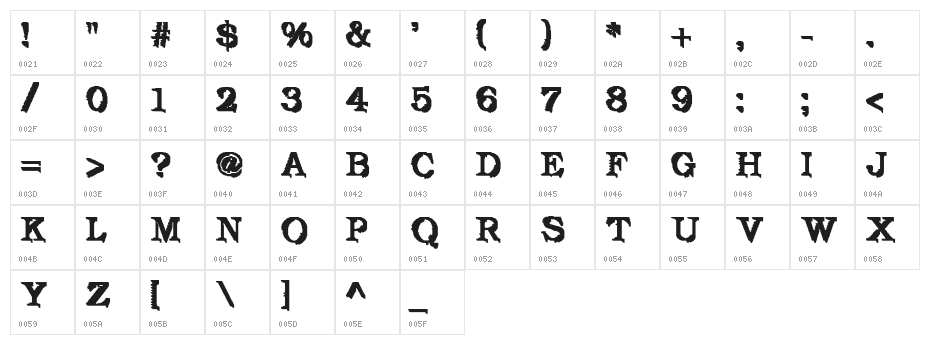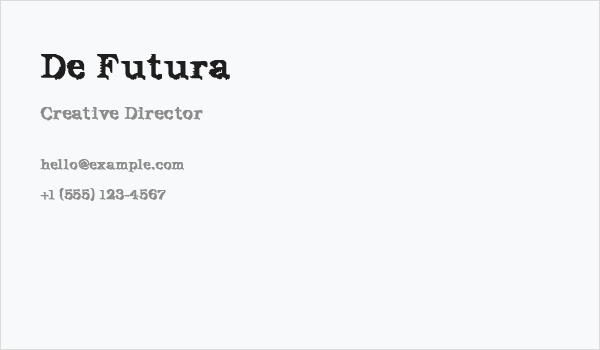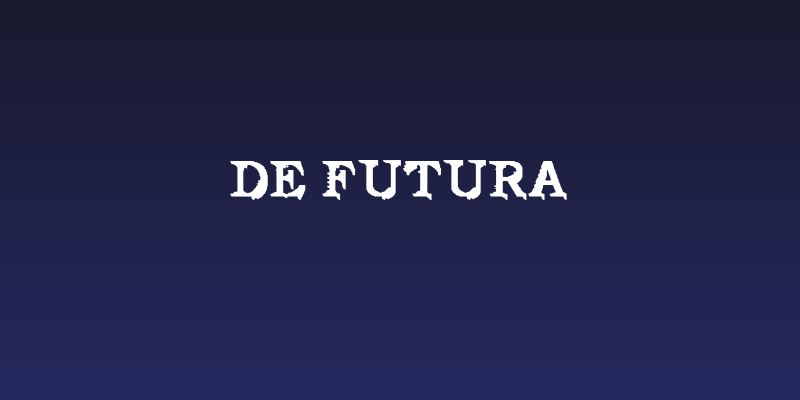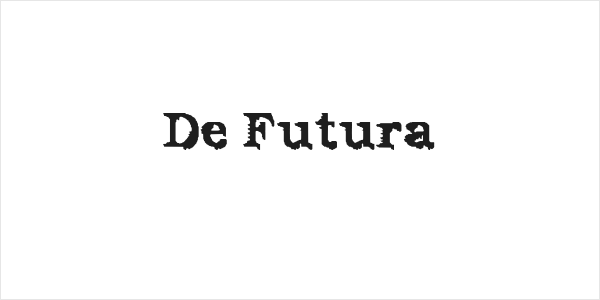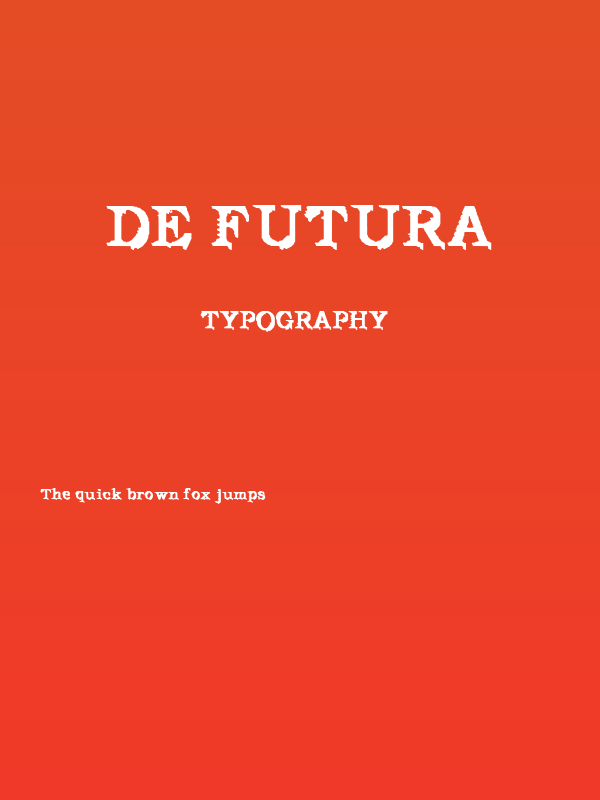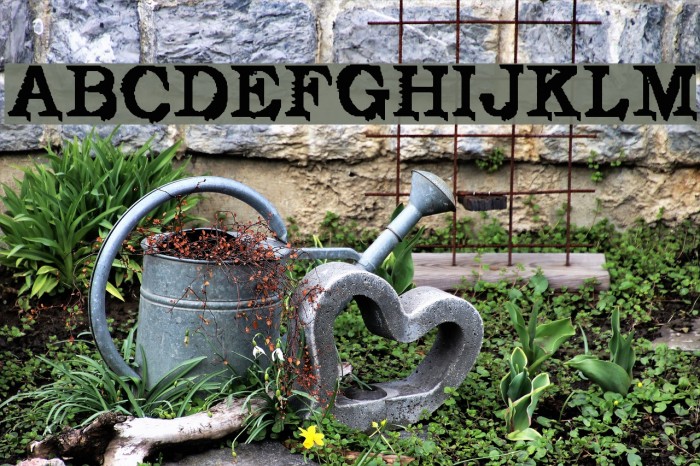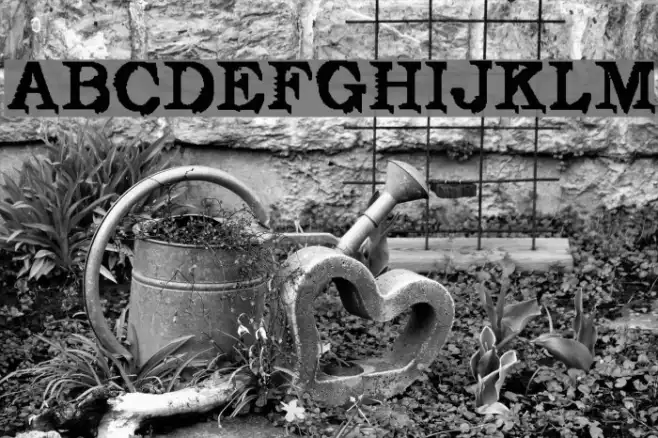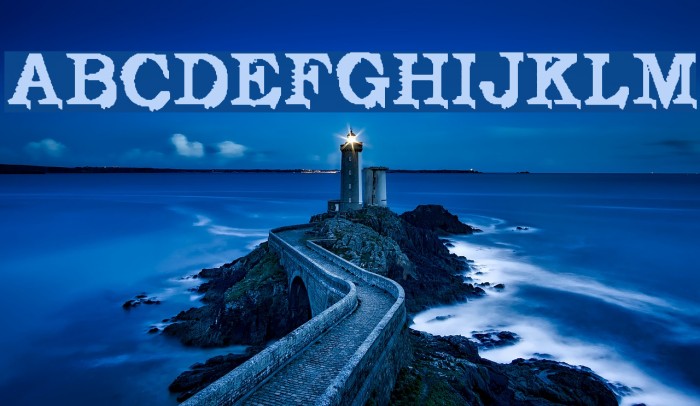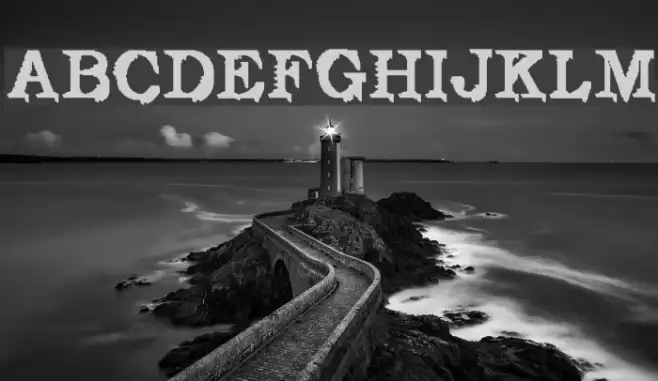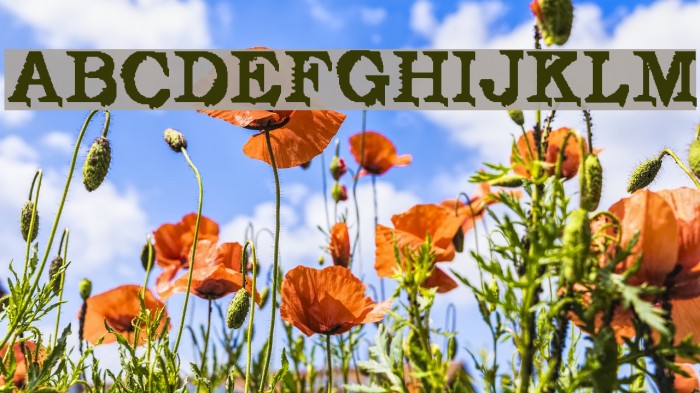
De Futura Font
| Gesamtstil | Vintage |
| Vorgeschlagene Projekte | Ideal for posters, album covers, vintage-themed designs, and branding projects that require a strong, artistic impact. |